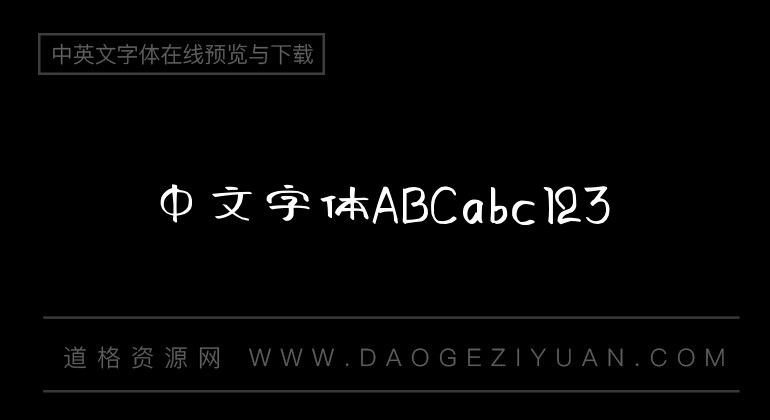
阿朱泡泡体是一种可爱、圆润的中文字体。它的字形有点像气泡,每个字都带有圆滑的边角和丰富的线条变化,使得它看起来非常生动活泼。这种字体适用于各种设计场合,例如海报、广告、logo等等。阿朱泡泡体常常被用来表达可爱、轻松、温暖的感觉,非常适合用来设计儿童、家居、食品等场合的宣传材料。文件名:AZhuPaoPaoTi-2.ttf
阿朱泡泡体是一款非常不错的手写艺术字体,具有很好的视觉感,适合于文化类的宣传设计、商业类品牌的广告和产品包装设计以及个性化文字排版等较多场景。